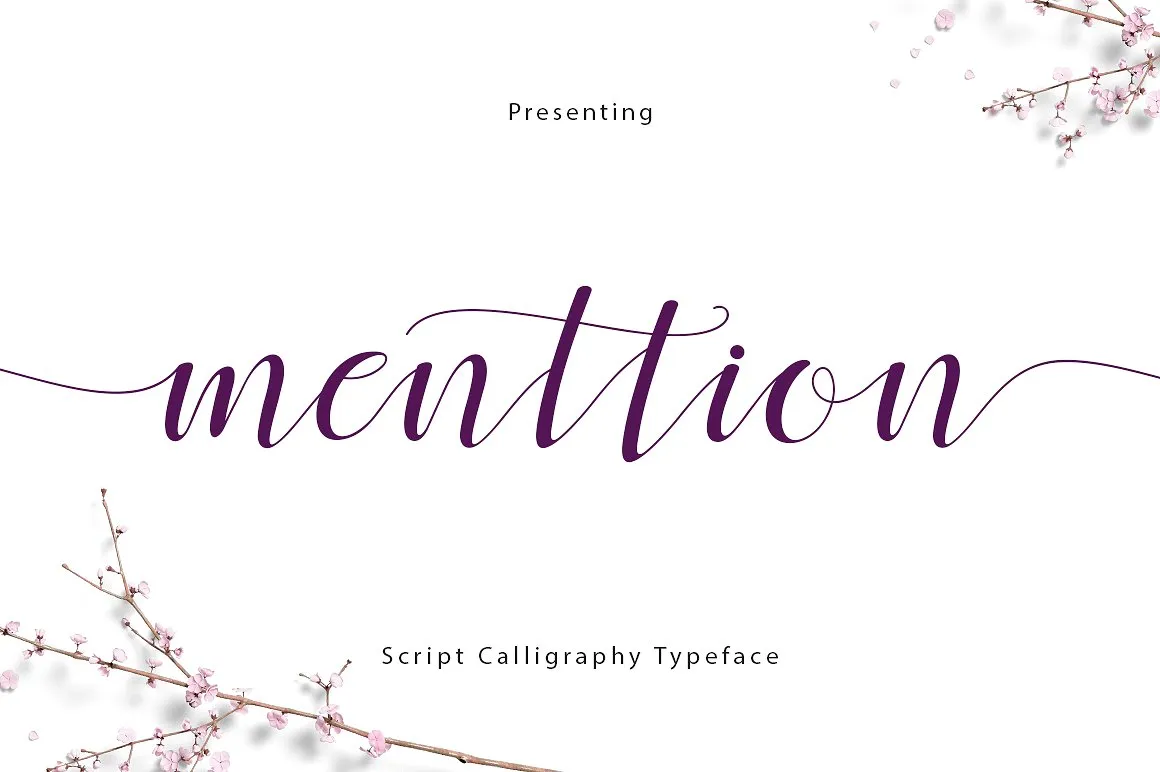
Menttion Script Font
Descobrimos uma nova fonte chamada Menttion Script Font para a categoria de Calligraphy Fonts. Desenvolvida pelo designer 178-MC, essa fonte premium está disponível gratuitamente para download hoje no Creativemarket. Menttion Script é um estilo elegante e sofisticado, projetado para transmitir elegância e estilo. Com seu traçado fino, feminino e descontraído, esta fonte se destaca não apenas na moda, mas também em marcas de e-commerce, blogs que seguem tendências ou qualquer negócio que queira parecer aconchegante e chic. Essa font é perfeita para adicionar um toque sofisticado às suas peças digitais. Ela trará elegância sem comprometer seu charme próprio. Mergulhe nesta oportunidade de fazer seus designs ainda mais especiais e elegantes. Não deixe essa chance passar, experimente o Menttion Script hoje mesmo.